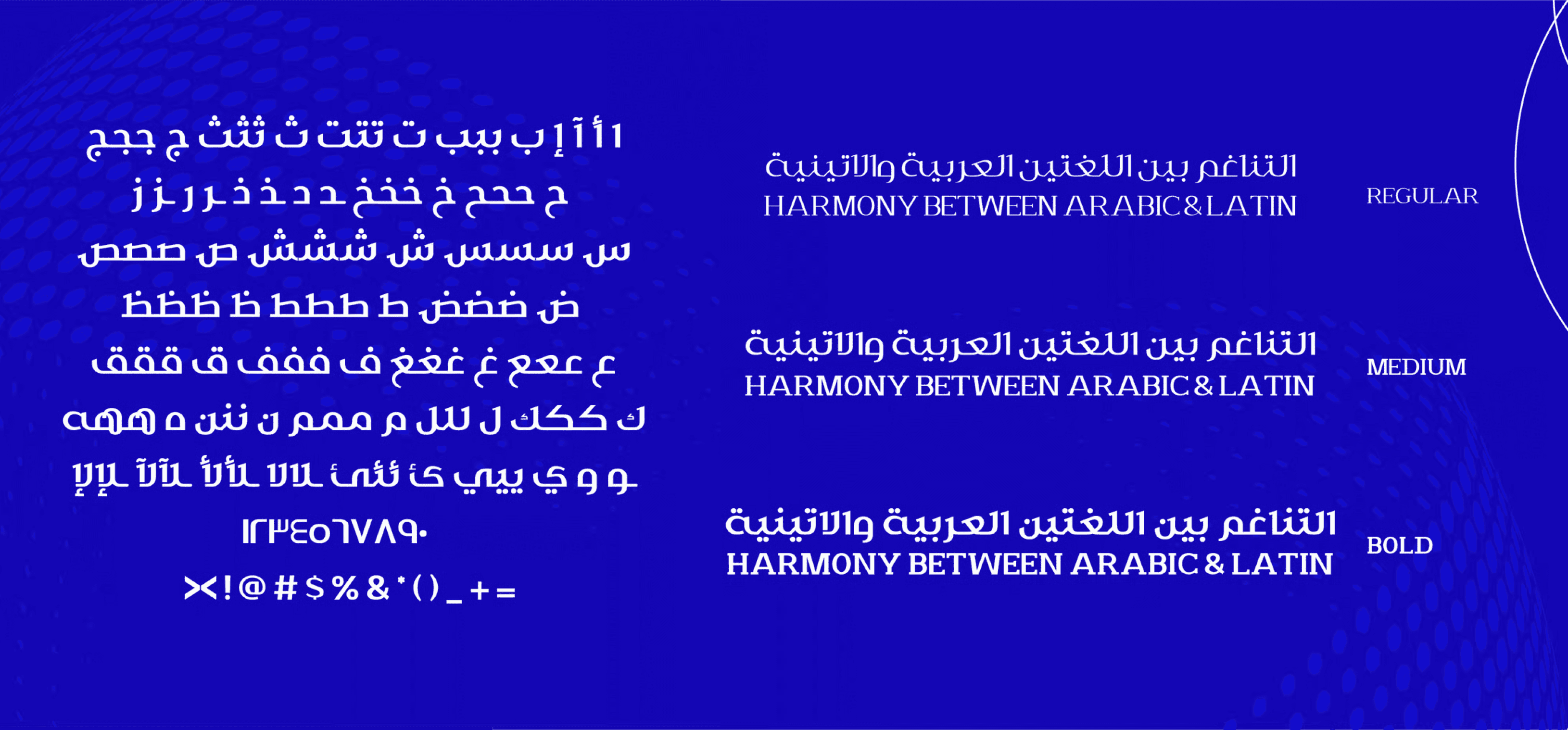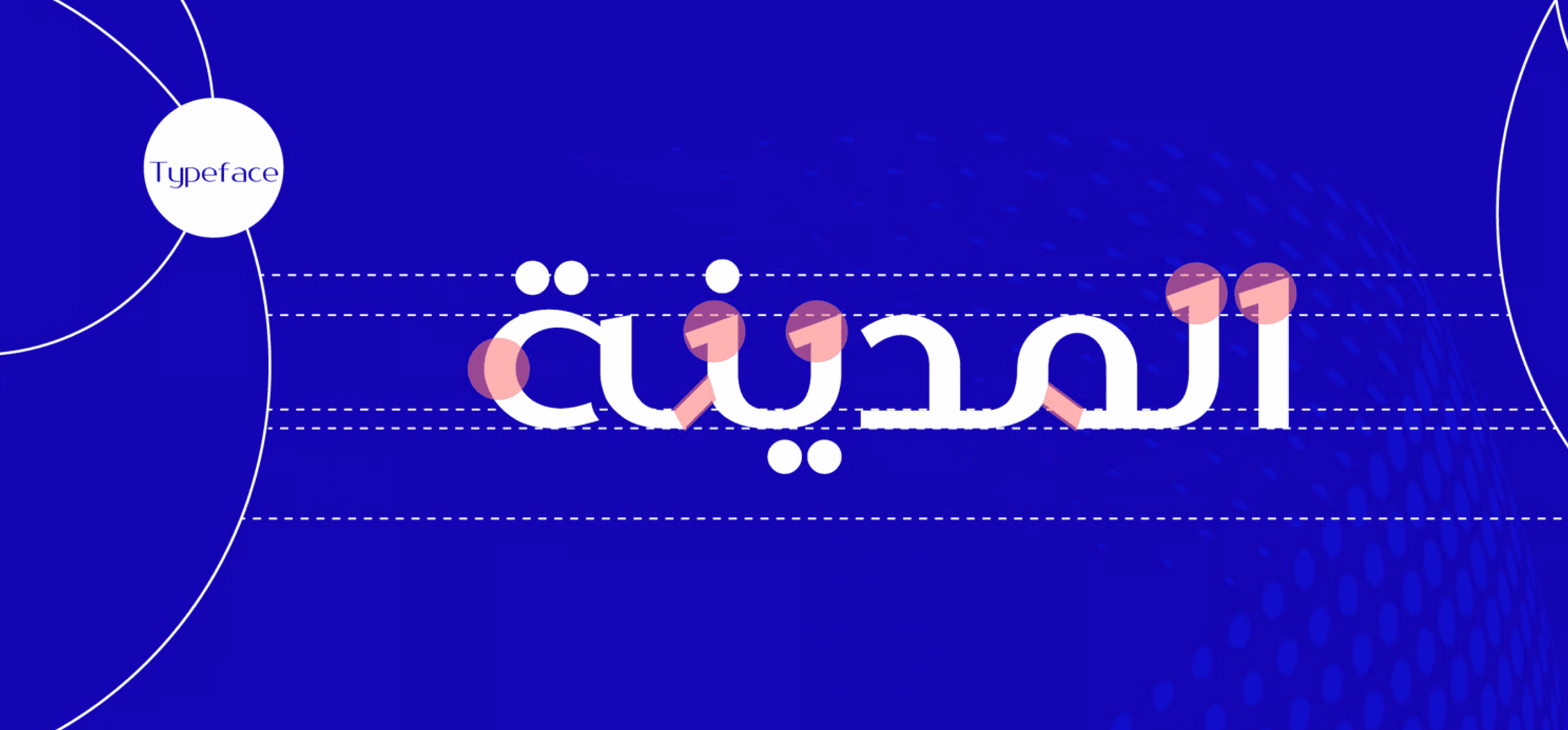
خط طباعي عربي ثنائي اللغة يتميز بتصميم هندسي متوازن يجمع بين التناسق والبساطة، ويمنح النصوص مظهرًا عصريًا واحترافيًا. مناسب لاستخدامات الشعارات، العناوين، الهويات البصرية، وإعلانات السوشيال ميديا، كما يتكامل بسلاسة مع واجهات المواقع الإلكترونية وتطبيقات الهواتف الذكية.
يتماشى الخط مع أعمال الشركات، القنوات الإعلامية، الصحف، والمجلات، ويعزز تجربة القراءة في المجالات الطباعية والرقمية على حد سواء.